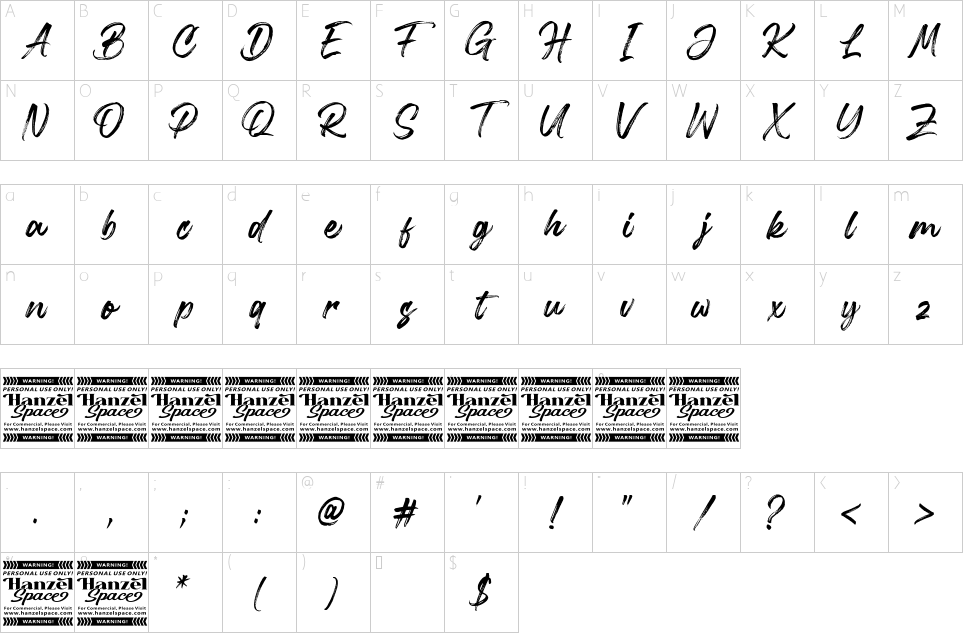
A Arthemis é uma fonte elegante e arquitetônica, ideal para qualquer projeto que exige um toque sofisticado e elegante. Desenvolvida por Hanzel Space, esta fonte pode ser facilmente usada em ambientes Windows e Mac, permitindo que você personalize sua identidade visual ou adorne qualquer obra de arte digital. Com um design minimalista e elegante, a Arthemis atende perfeitamente a quem busca uma fonte moderna e sofisticada, que se adequa perfeitamente a qualquer tipo de layout gráfico, desde design de gráficos até design editorial. Sua facilidade de uso e alta qualidade de impressão garantem que ela seja uma opção confiável e versátil. Com 1,066 downloads, a Arthemis se transforma em uma fonte de confiança para aqueles que procuram uma fonte de qualidade e estilo.